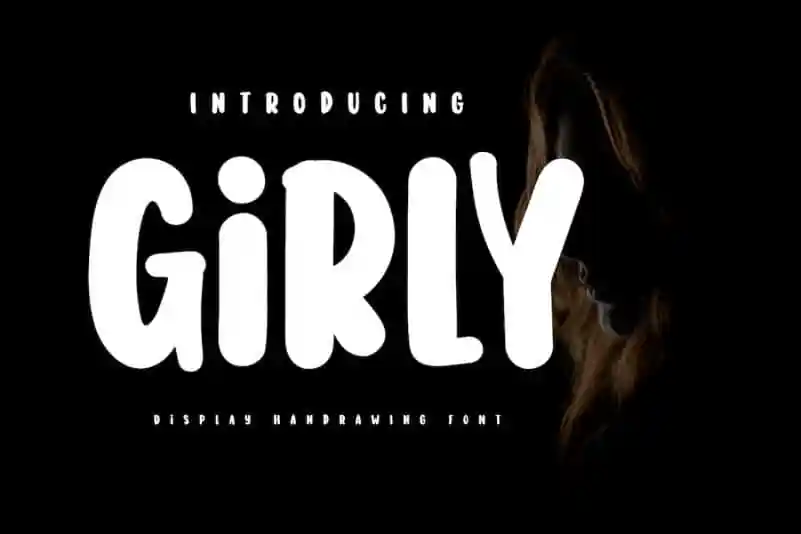
Girly Display Font é uma fonte criada pelo designer twinletter com um tema de escrita à mão forte e única, projetado para criar um impacto distintivo em qualquer projeto design. Suas linhas robustas combinadas a uma personalidade delicadamente suave resultam num impressionante conjunto que pode parecer relaxado e elegante ao mesmo tempo. Ideal para adicionar um toque de charme aos teus designs, esta fonte é perfeita para quem deseja dar um toque especial a qualquer projeto gráfico ou layout. Com sua versatilidade e a capacidade de criar uma sensação única em qualquer design, o Girly Display Font oferece-lhe a liberdade de fazer algo diferente e original. Que tal usar essa fonte para adicionar um pouco mais de personalidade à tua próxima criação?